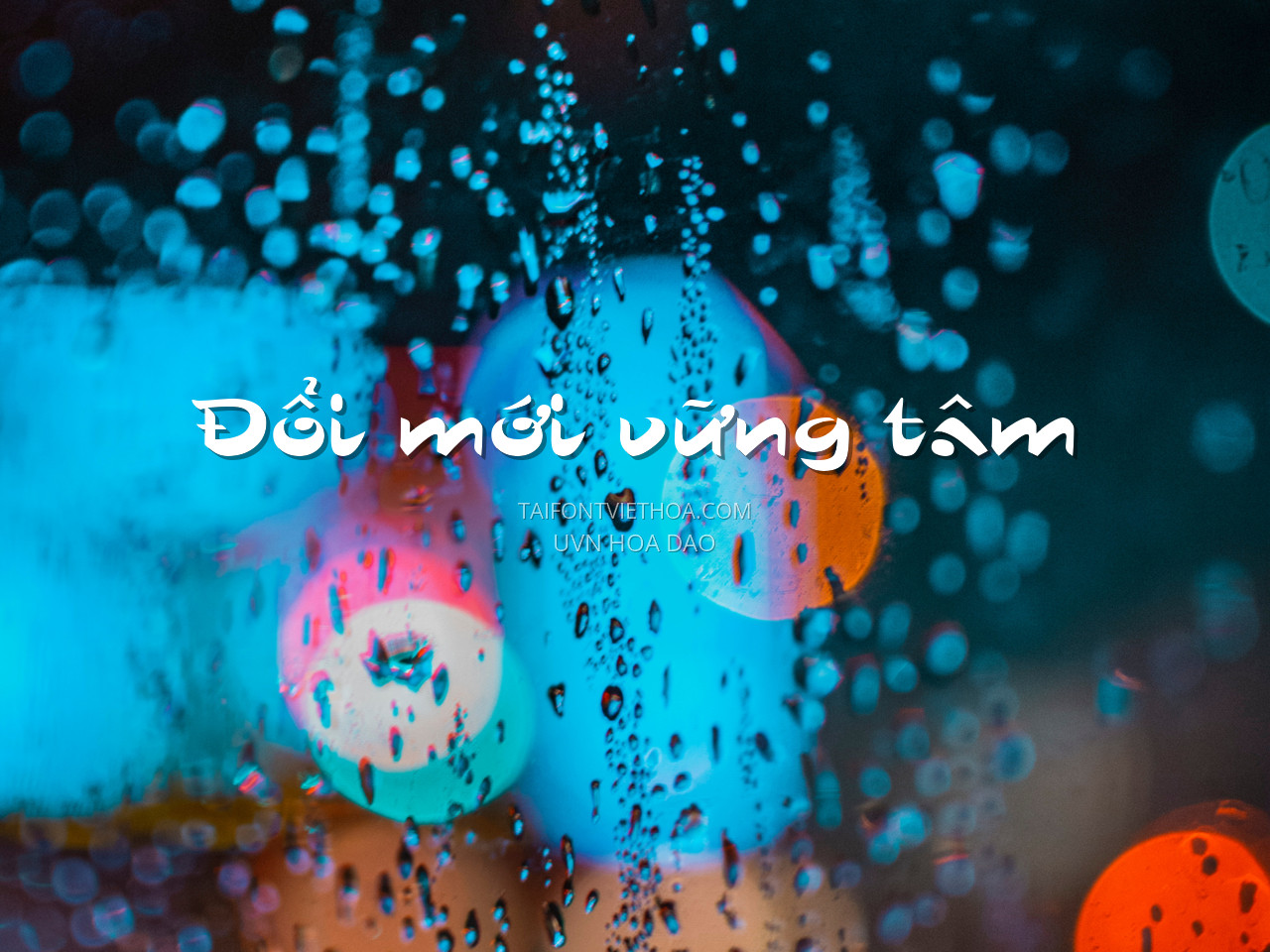
Font việt hóa UVN Hoa Dao
Giới thiệu về font UVN Hoa Dao
UVN Hoa Dao là một font chữ mang đậm không khí Tết cổ truyền Việt Nam, được lấy cảm hứng từ hình ảnh hoa đào – biểu tượng của mùa xuân miền Bắc và khởi đầu may mắn. Phong cách thiết kế nhẹ nhàng, mềm mại nhưng vẫn rõ ràng giúp font gợi nên cảm giác tươi vui, thân thuộc và đậm đà bản sắc văn hóa dân tộc. UVN Hoa Dao thường được sử dụng trong các ấn phẩm Tết, thiệp chúc mừng năm mới, bao lì xì hoặc các chiến dịch truyền thông mùa lễ hội. Font được sưu tầm và chia sẻ bởi thành viên Font Chuẩn, đồng thời được taifontviethoa.com chọn lọc và ứng dụng thực tế trong các dự án thiết kế xuân, quảng cáo lễ hội và truyền thông văn hóa.
Đặc điểm thiết kế và ứng dụng của UVN Hoa Dao
Font UVN Hoa Dao có kiểu chữ viết tay cách điệu, với các nét cong nhẹ, mềm mại như cánh hoa đào bay trong gió. Các ký tự được thiết kế với độ uốn lượn vừa phải, tạo sự sinh động và biểu cảm cao. Font hỗ trợ tiếng Việt đầy đủ, dễ sử dụng trong cả in ấn và hiển thị kỹ thuật số, đặc biệt là các thiết kế Tết cổ truyền hoặc sản phẩm mang hơi hướng dân gian.
Ứng dụng lý tưởng: thiệp Tết, bao lì xì, tiêu đề banner xuân, poster lễ hội, hộp quà Tết, infographics văn hóa dân tộc. Ngành nghề phù hợp: quảng cáo lễ hội, thiết kế truyền thống, ấn phẩm văn hóa, sản phẩm tiêu dùng mùa Tết và truyền thông thương hiệu trong dịp Xuân.